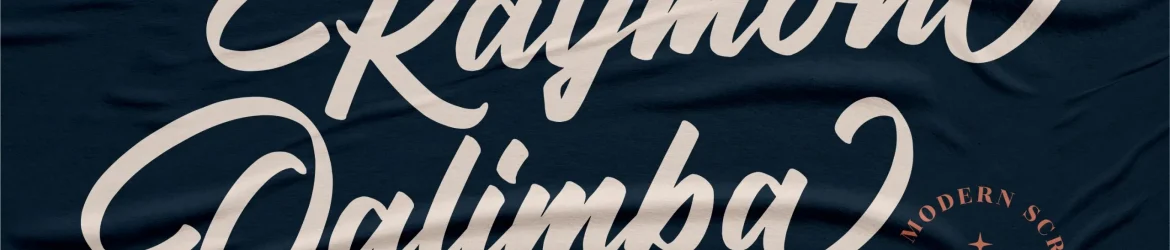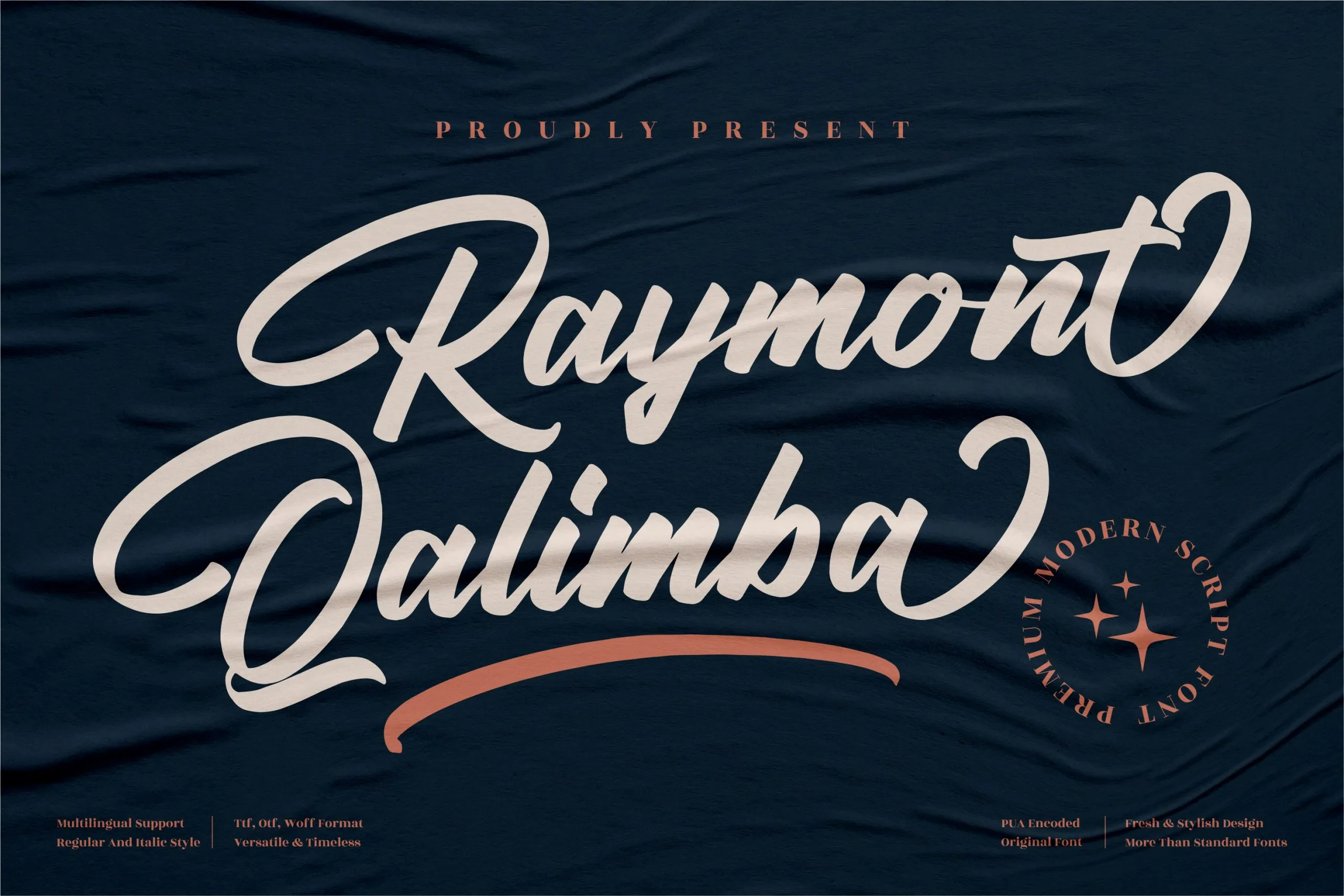
Raymont Qalimba Font
Essa font é perfeita para quem busca uma assinatura diferenciada, com personalidade e sofisticação. A Raymont Qalimba Font é um exclusivo encargo que se adequa a diversos tipos de projetos, desde logotipos e identidades corporativas até designs de embalagens e pacotes de produto. Seja em itens cotidianos como chávenas ou sacolas de shopping, ou em criações mais carregadas de significado como cartões de convite para casamentos especiais ou capas de livros, a Raymont Qalimba Font oferece um toque de elegância e sofisticação. Suavidade na escrita combinada com destreza para destacar mensagens importantes são características que tornam esta fonte uma escolha ótima para qualquer projeto que exige uma assinatura de alta qualidade. Desfrute criando experiências visualmente impactantes, utilizando a Raymont Qalimba Font para um toque único e sofisticado em seus projetos.